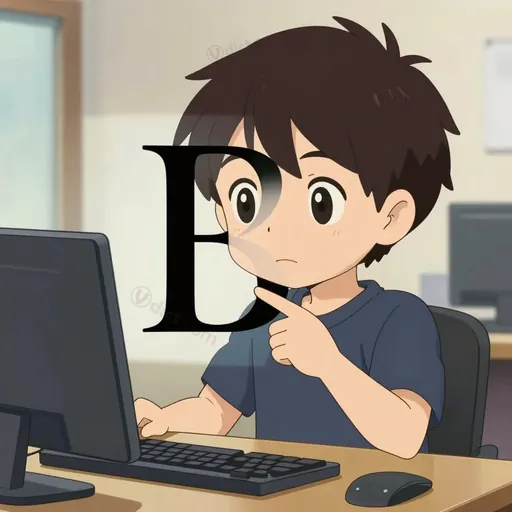
bodoni font
Danh từ: Kiểu chữ Bodoni một kiểu chữ (typeface) nguồn gốc từ thiết kế thế kỷ 18 của Gianbattista Bodoni. được đặc trưng bởi hình dạng đều đặn, các chân chữ (serif) mảnh như sợi tóc các nét xuống (downstroke) dày.
• (Tựa đề cuốn sách được in bằng kiểu chữ bodoni cổ điển để tạo vẻ thanh lịch.)
• (Nhiều tạp chí thời trang sử dụng kiểu chữ bodoni cho các tiêu đề của họ độ tương phản cao vẻ ngoài tinh tế của .)
• Bodoni font thường được dùng trong thiết kế cao cấp, sách quảng cáo để truyền tải sự sang trọng cổ điển.
• The wedding invitation used a bodoni font to emphasize the formal and romantic tone. (Thiệp cưới sử dụng kiểu chữ bodoni để nhấn mạnh giọng điệu trang trọng lãng mạn.)
• Bodoni font độ tương phản cao giữa nét dày nét mảnh, dễ đọc trong các văn bản ngắn nhưng có thể gây khó khăn khi in ấn với kích thước nhỏ.
• Due to its thin serifs, the bodoni font is best used for headings rather than body text. (Do các chân chữ mảnh, kiểu chữ bodoni thích hợp dùng cho tiêu đề hơn nội dung chính.)
• Bodoni (n): tên gọi tắt của kiểu chữ Bodoni.
• I prefer Bodoni over Times New Roman for its elegance. (Tôi thích Bodoni hơn Times New Roman vẻ thanh lịch của .)
• Kiểu chữ serif cổ điển: một loại kiểu chữ chân chữ (serif) mang phong cách truyền thống.
• Kiểu chữ Didot: một kiểu chữ tương tự Bodoni, cũng độ tương phản cao chân chữ mảnh.
• Set in bodoni: đặt (văn bản) bằng kiểu chữ Bodoni.
• The designer set the entire brochure in bodoni for a cohesive look. (Nhà thiết kế đặt toàn bộ tờ rơi bằng kiểu chữ bodoni để có vẻ ngoài nhất quán.)
• Use bodoni: sử dụng kiểu chữ Bodoni.
• She decided to use bodoni for the logo to evoke a sense of heritage. ( ấy quyết định sử dụng bodoni cho logo để gợi lên cảm giác về di sản.)
• Bodoni serif: chân chữ kiểu Bodoni, chỉ một đặc điểm thiết kế cụ thể.
• The bodoni serif is so fine that it can break in small print. (Chân chữ kiểu Bodoni mảnh đến mức có thể bị đứt trong bản in nhỏ.)
A designer selects the Bodoni font for a book cover.